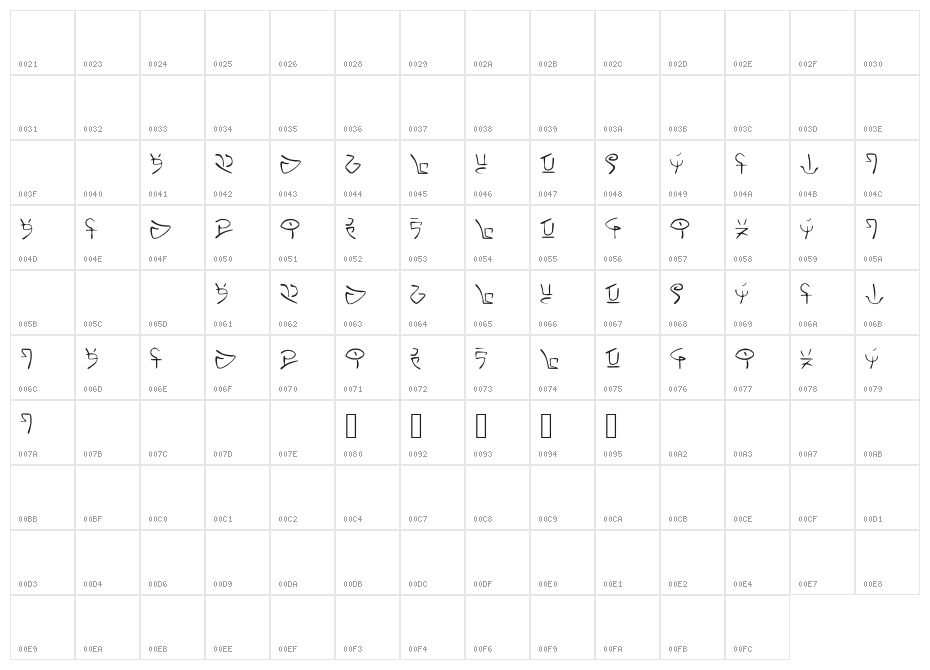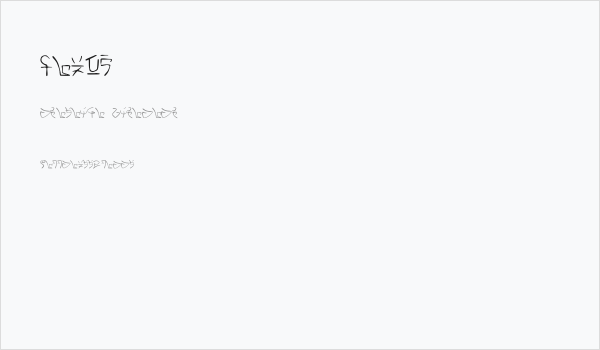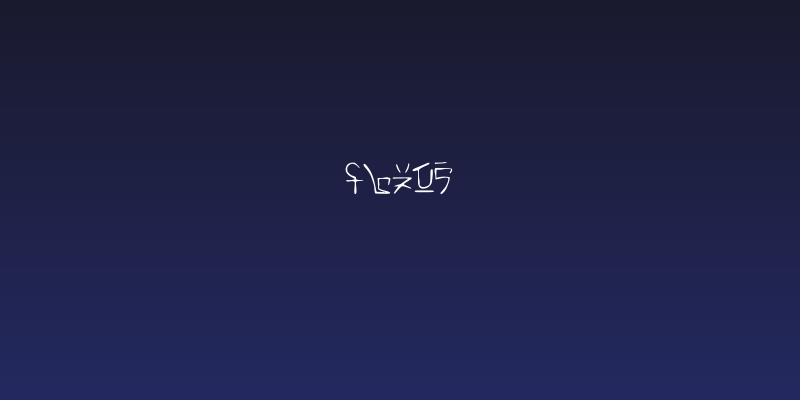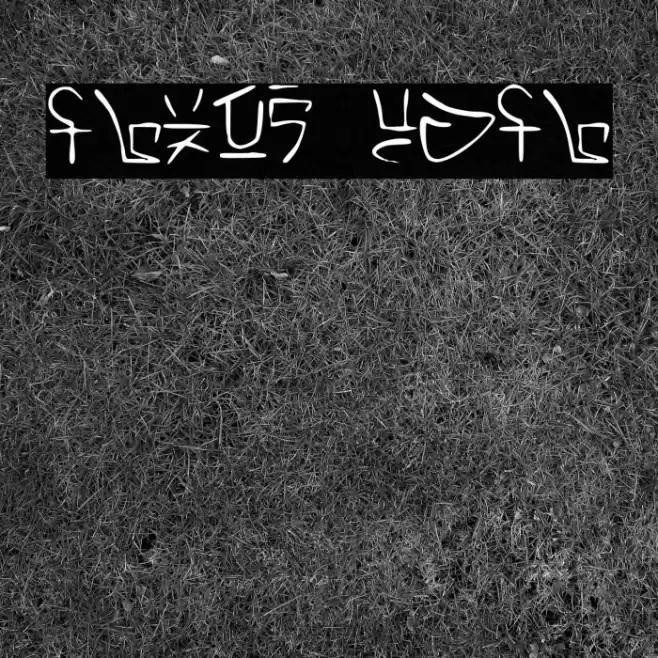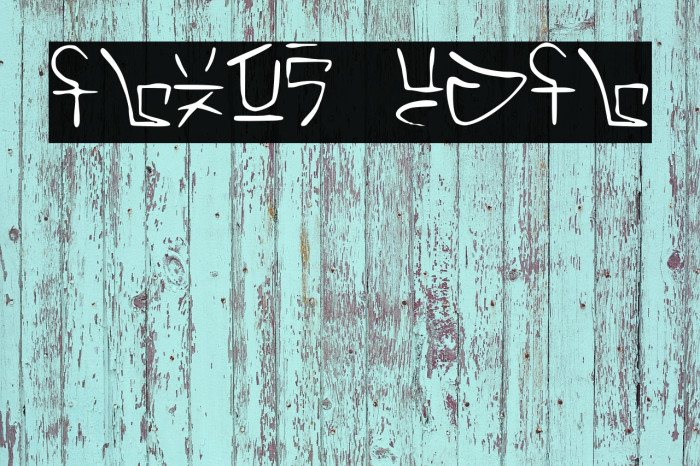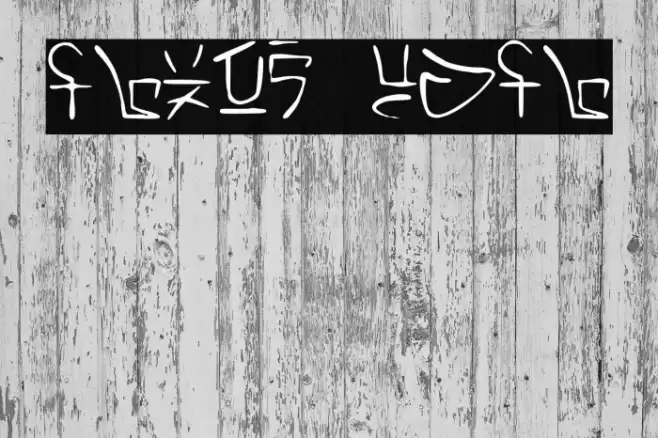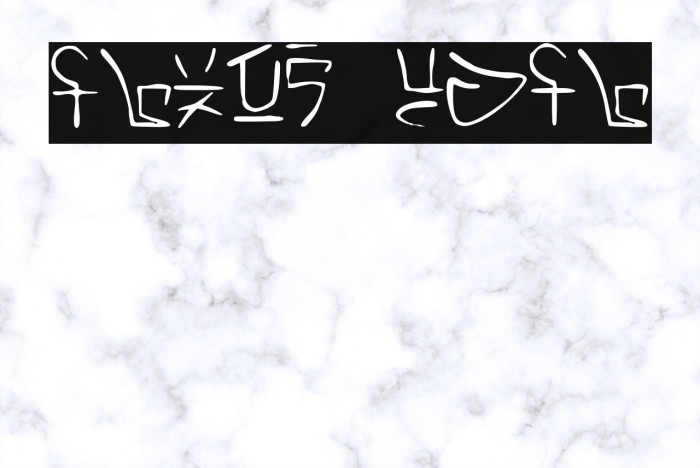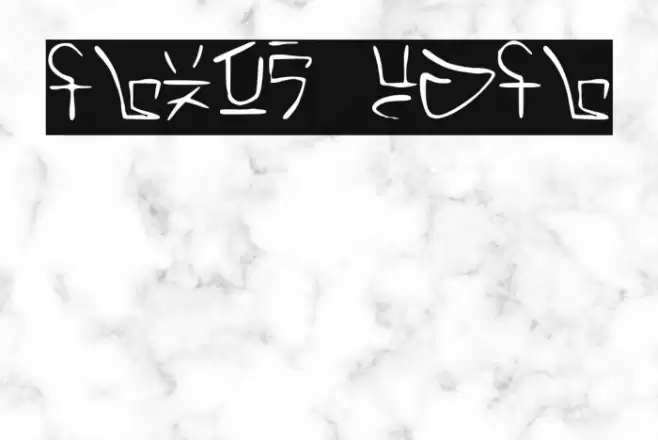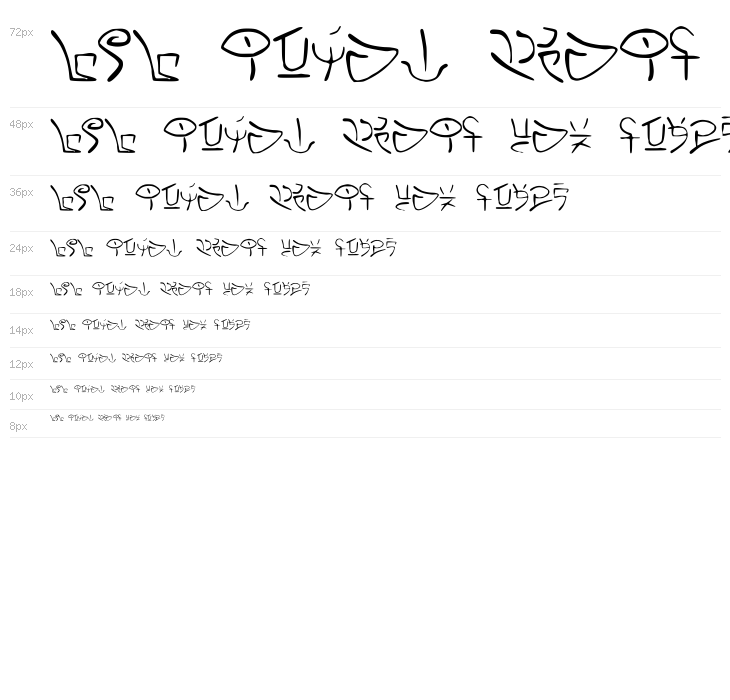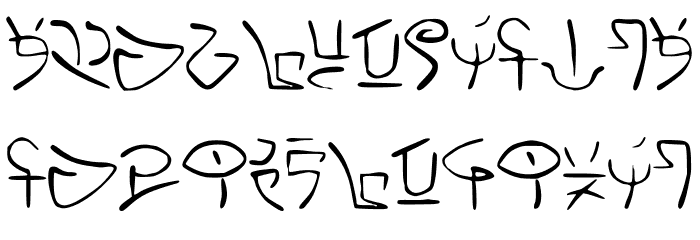
Nexus Font
| Cas d'utilisation | Logos, Posters, Thematic Artwork |
| Projets proposés | Ideal for fantasy-themed designs, escape room branding, or any project requiring a mystical or ancient aesthetic. |